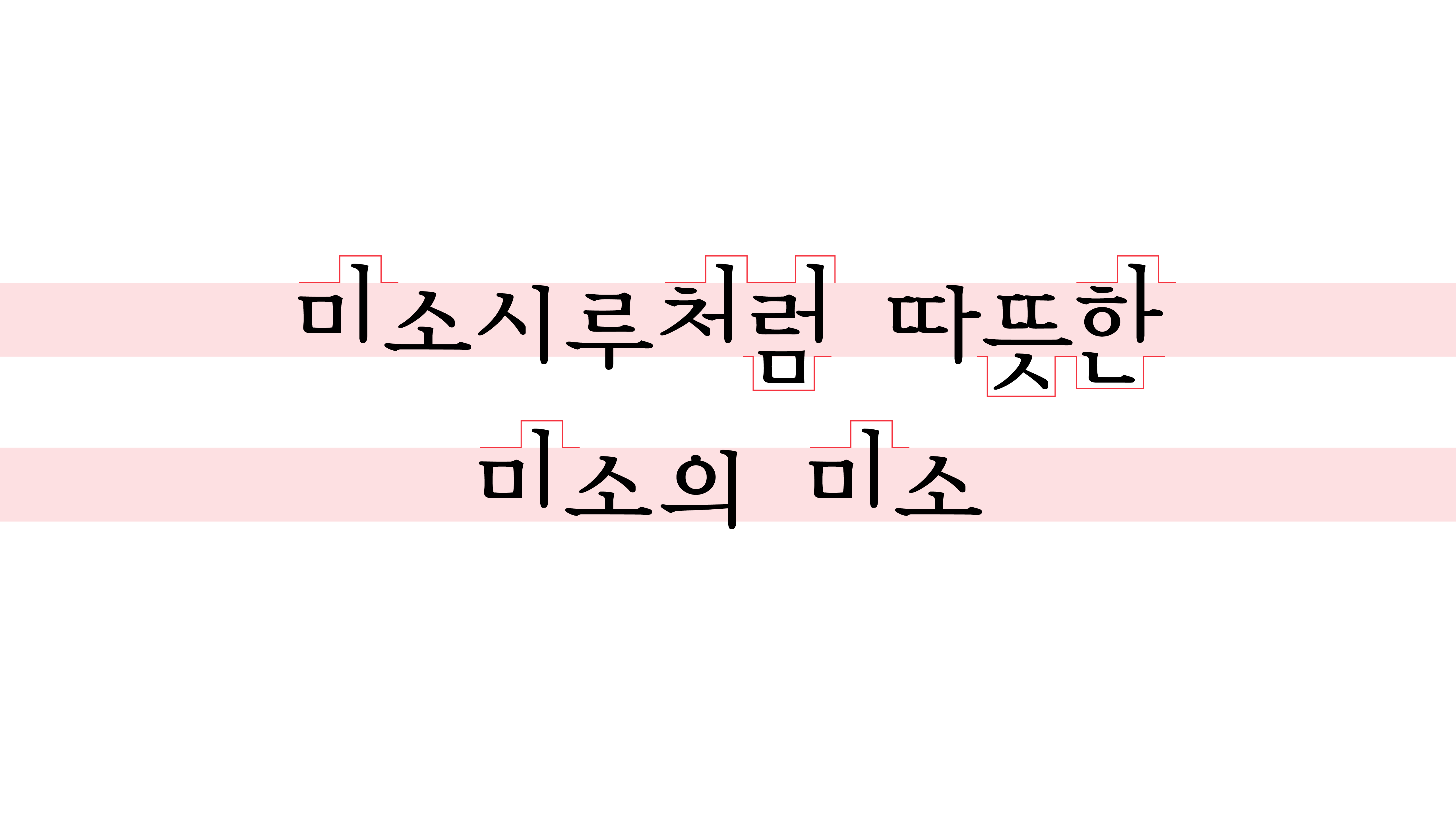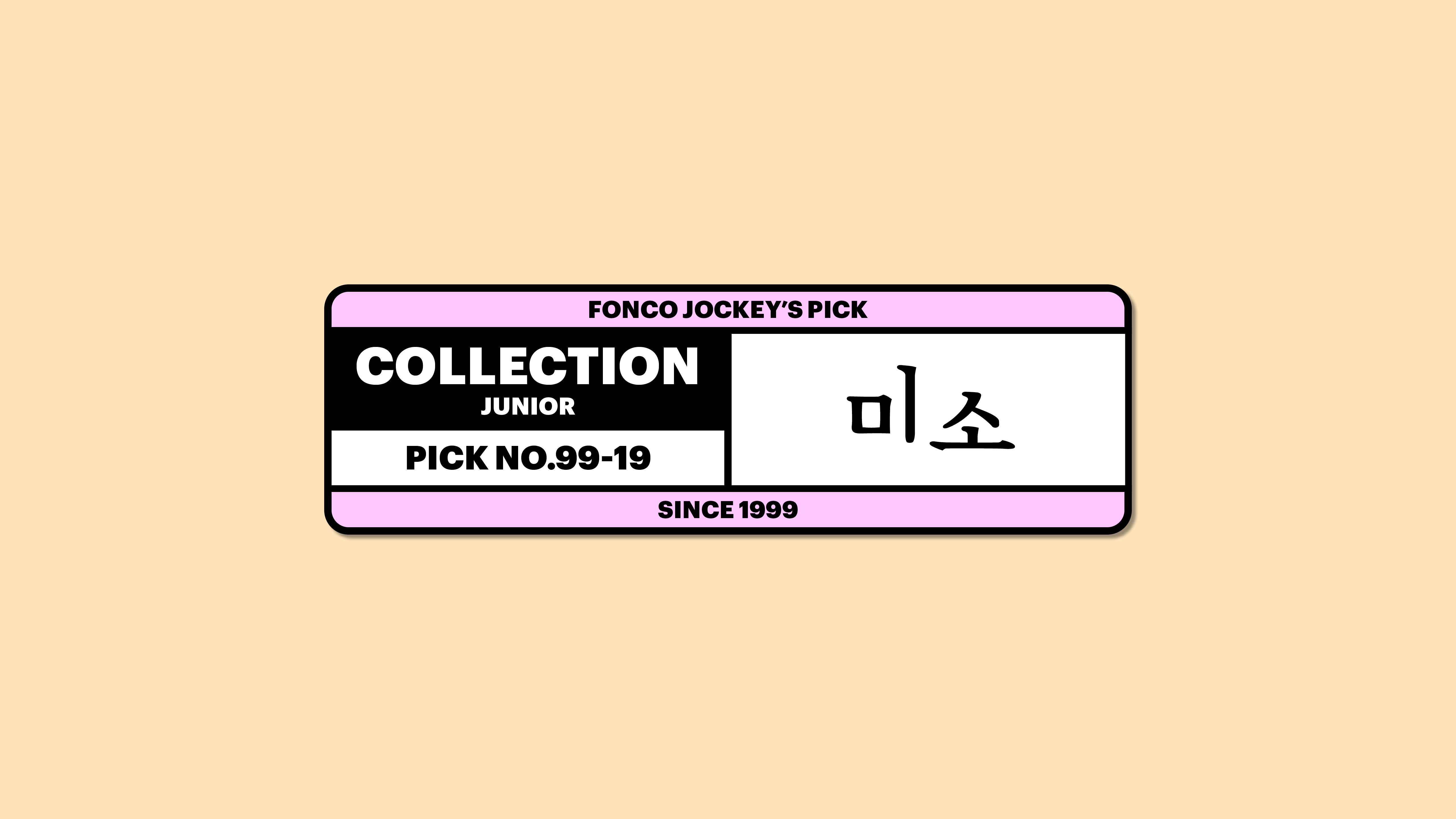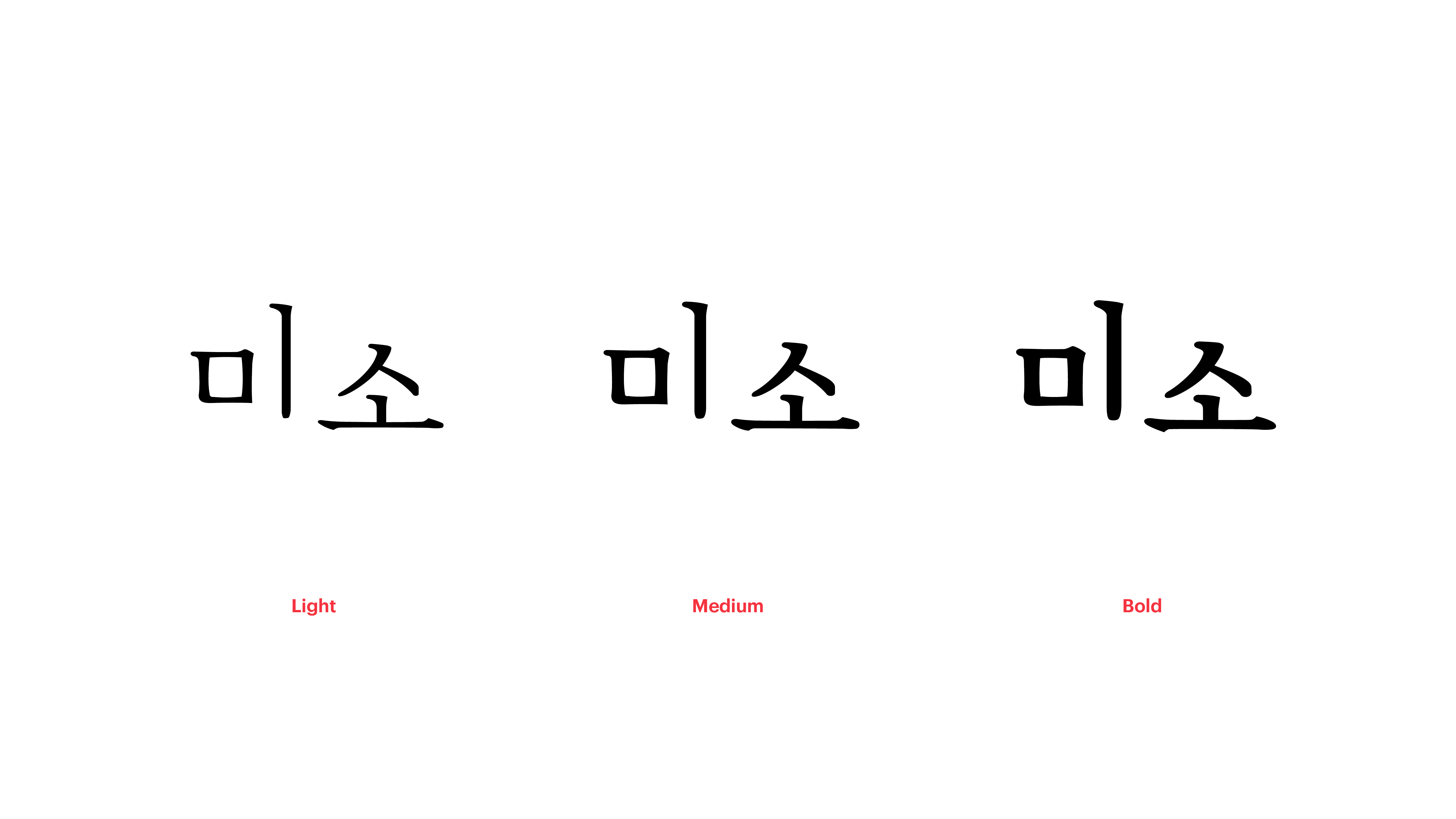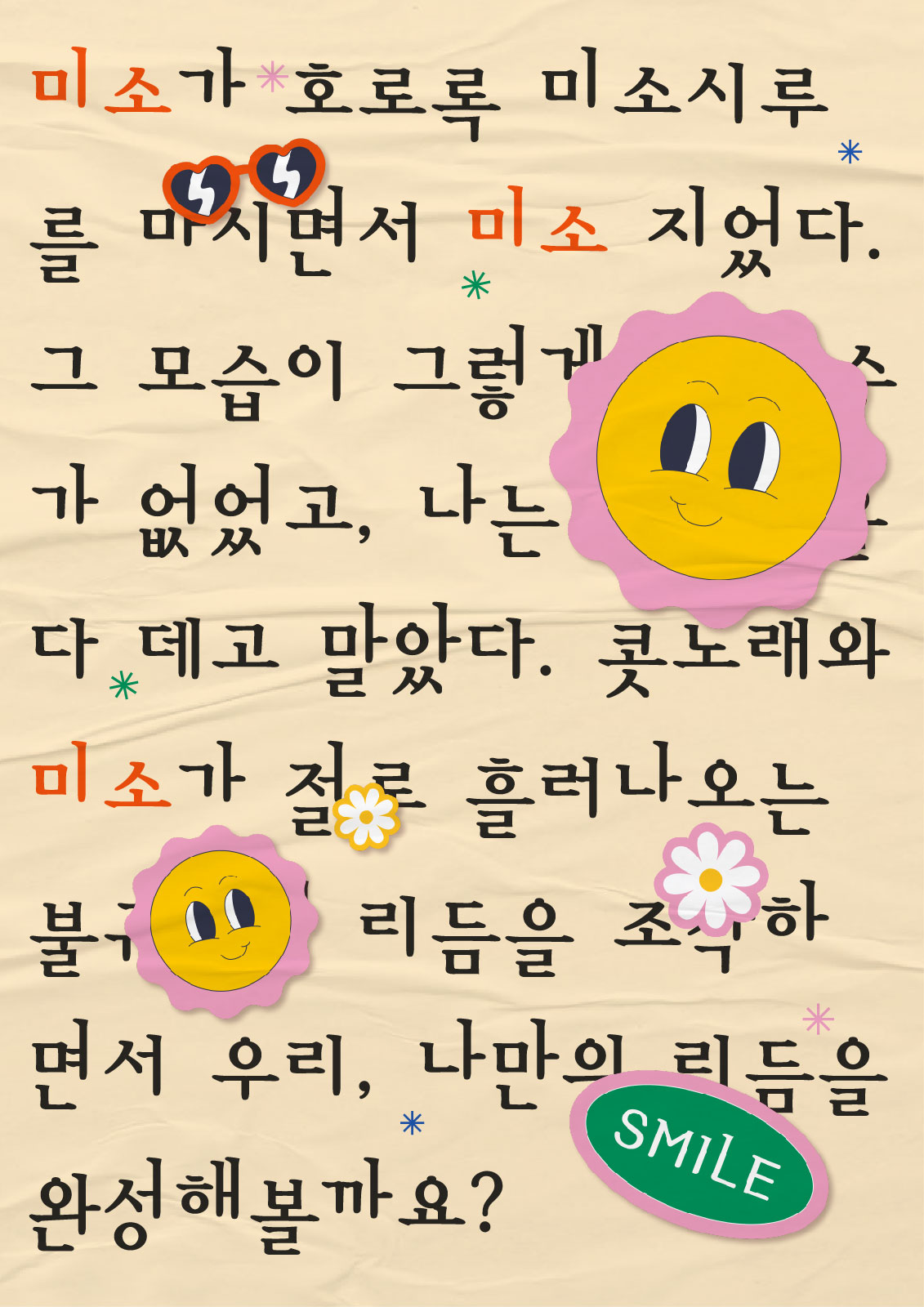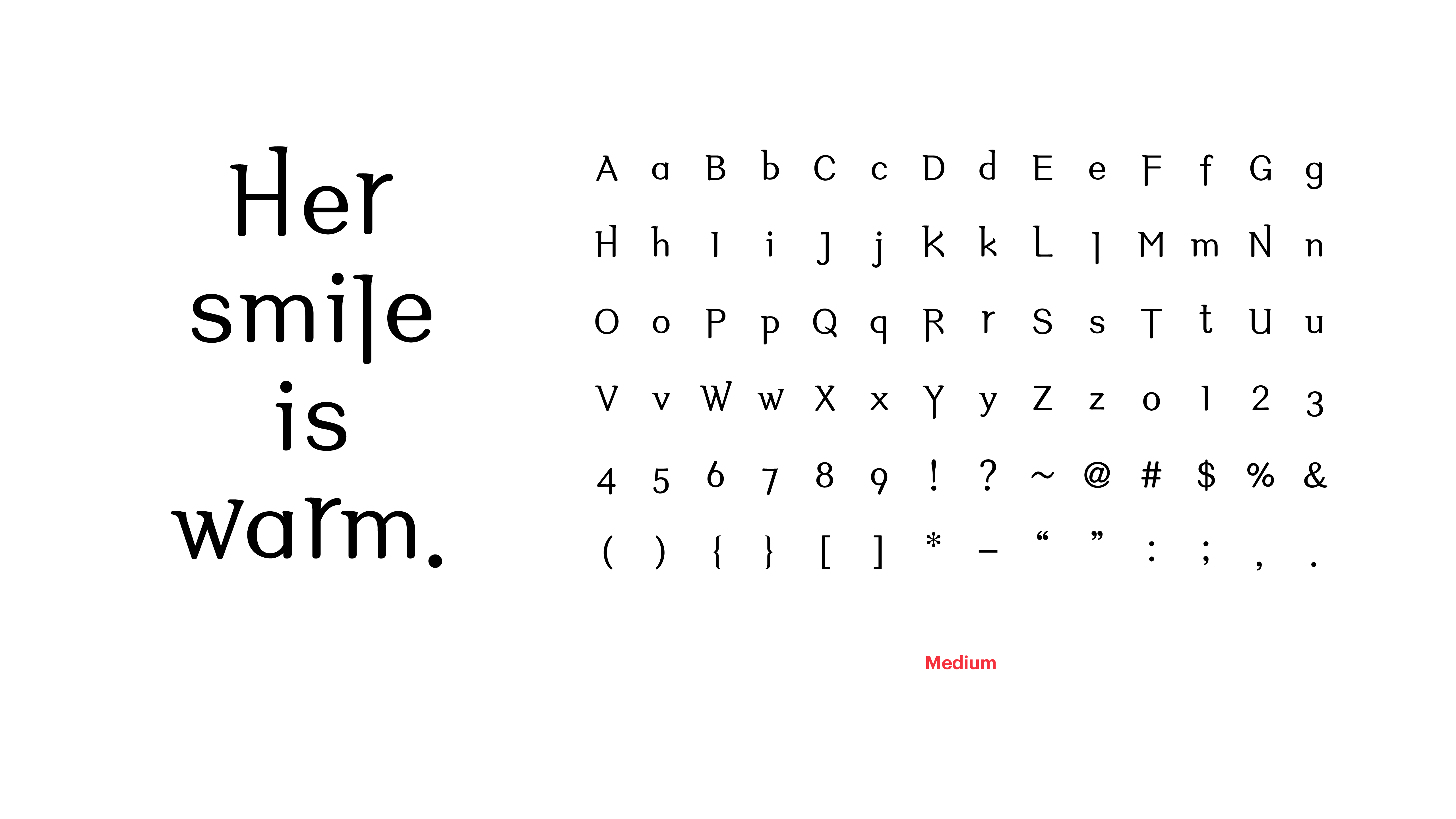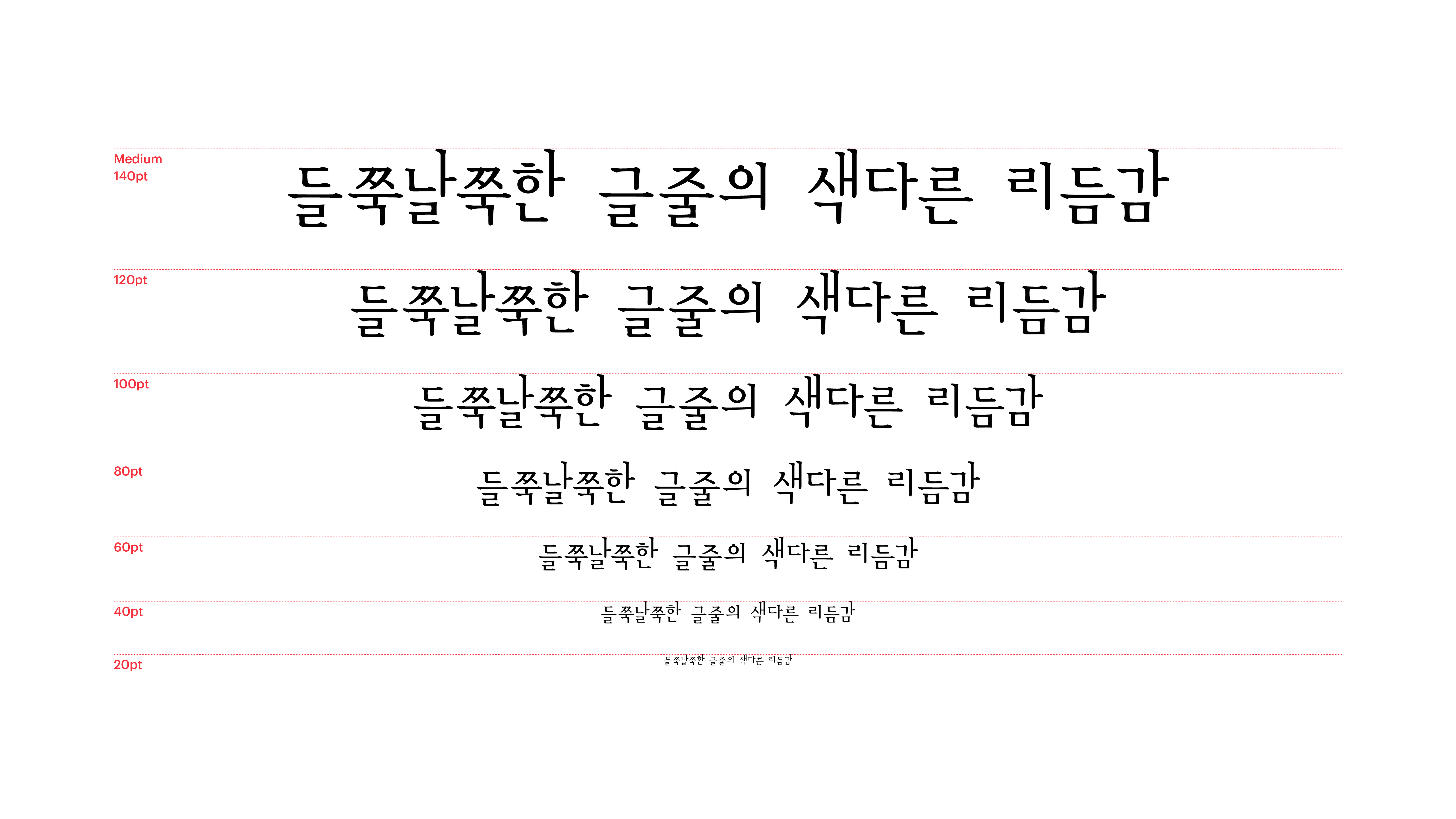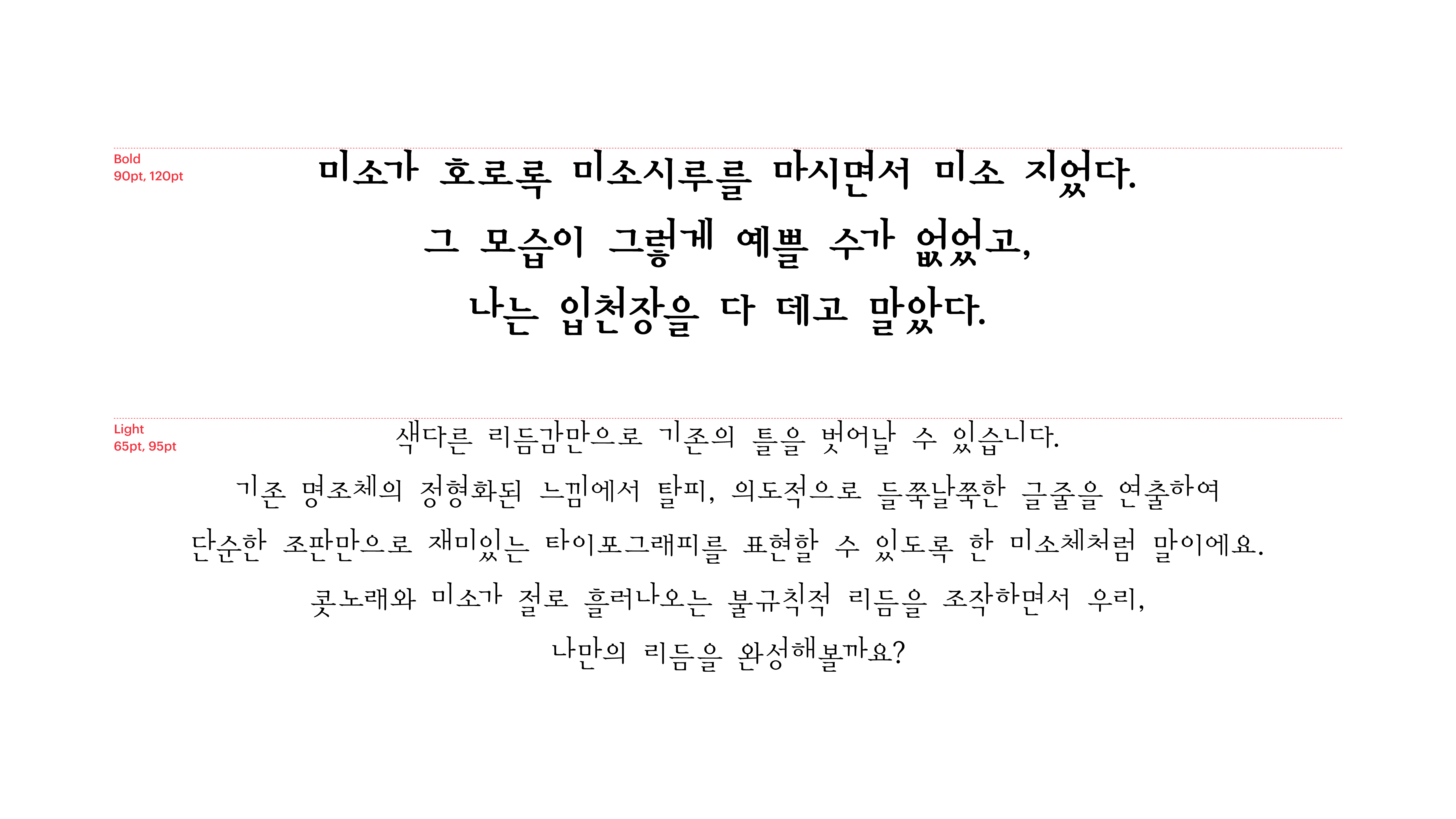
미소
Yoon 미소
색다른 리듬감만으로 기존의 틀을 벗어날 수 있습니다. 기존 명조체의 정형화된 느낌에서 탈피, 의도적으로 들쭉날쭉한 글줄을 연출하여 단순한 조판만으로 재미있는 타이포그래피를 표현할 수 있도록 한 미소체처럼 말이에요. 콧노래와 미소가 절로 흘러나오는 불규칙적 리듬을 조작하면서 우리, 나만의 리듬을 완성해볼까요?